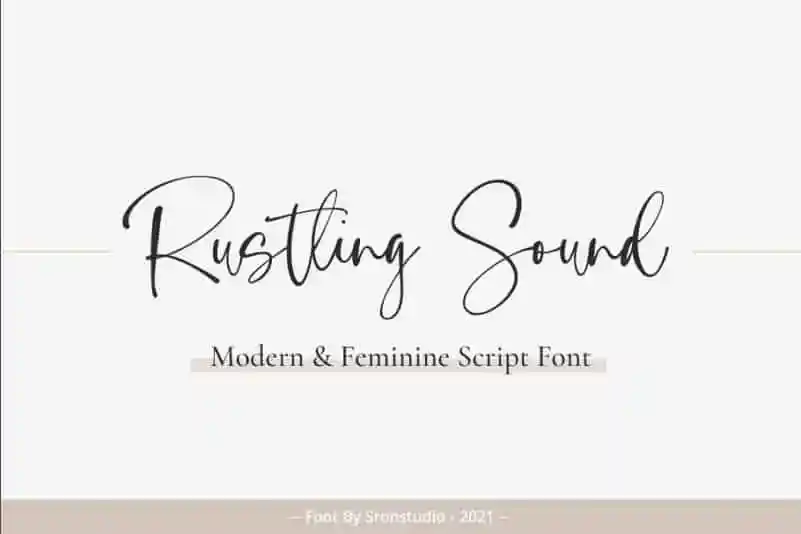
Rustling Sound Script Font – Download Grátis
A Rustling Sound Script Font é uma excelente opção para quem procura uma letra elegante para trabalhos variados. Esta fonte vem com tradução multilíngue, alternativas e ligaturas exclusivas do designer drizy! Perfeita tanto para marcas de marca, convites, cartões de visita, design de casamento, posts nas redes sociais, anúncios, embalagens de produtos, designs dos produtos, rótulos, fotografia ou até mesmo o uso como um feixe d’água em eventos especiais. Com sua forma suave e agradável ao toque, esta fonte é ideal para qualquer projeto gráfico que exija um toque especial e personalizado. Seja você criando um design de marca inovador, decorando um site ou simplesmente querendo adicionar uma nota única em seu próximo projeto visual, Rustling Sound Script Font está aqui para te ajudar a destacar-se da multidão.